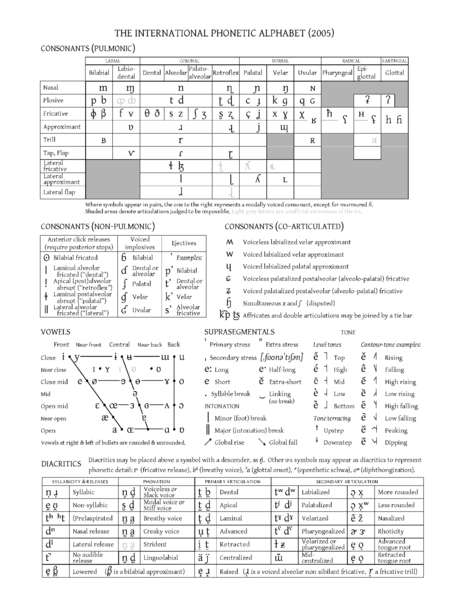
国际音标
国际音标(The International Phonetic Alphabet,简称 IPA),早期又称万国音标,是一套用来标音的系统,以拉丁字母为基础,由国际语音学学会设计来作为口语声音的标准化标示方法。国际音标的使用者有语言学家、言语治疗学家、外语教师、歌手、辞书学家和翻译学家等人。
按照国际音标的设计,它只可以分辨出口语里下列音质的对立成分:音位、语调以及词语和音节的分隔。若要表示诸如咬牙、咬舌和由唇颚裂所发出声音的音质,则有另一套获广泛使用的国际音标扩充系统(由国际语音学学会设计)。
直到2007年,国际音标共有107个单独字母,以及56个变音符号和超音段成分。国际语音学学会偶尔会增删一些符号,或者修正某些符号。
编制类型
国际音标的原则为一个音(或音段)一个符号。这表示,国际音标不会使用两个以上的字母来标示一个声音,除非它可以被视为一两个以上的声音的连续。国际音标通常也不会使用不同的字母来标示两个音,如果没有一个已知的语言将这两个音视为不同的音(选择性),且亦不会使用标示复音节的字母,如 <x> 在英语里表示 [ks] 此一子音复音节。此外,国际音标也没有会因上下文不同而不同音的字母,如英语(及其他大多数的欧洲语言)里的 <c> 。
国际音标的符号共有107个用来标示子音和元音的字母、31个用来更加细化声音的变音符号以及19个标示如音长、声调、重音与语调等的超音段成分。
国际音标中的一些与拉丁字母相同的辅音如 [p], [b], [t], [d], [k], [g], [m], [n], [f], [v], [s], [h], [z], [l], [w] 等已经为许多欧洲语言所使用的字母,在发音上与英语并无差别,而与拉丁字母相同的元音符号[a], [e], [i], [o], [u],它们的发音法则较接近西班牙语或意大利语中的发音,如[i]的发音为英文 piece 中的 i,而 [u] 为英文 food 中的 oo。
其他一些音标虽然与拉丁字母相同,如[j], [r], [c], 和 [y],它们的发音却和一般英语中的发音不太一样,而是来自其他的语言,例如 [j] 要发英语 yoke 的 y(等同德语或荷兰语的 j),而 [y] 的音却反而是和斯堪的那维亚语或古英语的 y 发音一样(等同于拼音的ü/yu/iu、粤语的于jy1、芬兰语的 y、德语的 y 或 ü、法语的 u,或荷兰语的 uu)。其主要的标音原则是一个符号代表一个音,因此不会有像英语中 sh 和 th 这样,两个子音字母组合来代表一个音的情况发生。
在国际音标表里,我们所看到的一些和拉丁字母相似,而只经过稍微改变的符号,它们的发音都很相似,例如卷舌音 ɳ 和齿龈音的 n,它们的发音及符号标示都差不多,除了前者右下角有向右的小勾,代表它是一个卷舌音。
附加于字母的变音符号(附加符号)则为每个语音做额外的描述,如下标 ̥ 加在子音之下,如 n̥ ,说明它是一个无声子音(清辅音)。另外还有一些特别的符号负责描述超音段的语音特征如重音、语调和声调,如元音后的 ː 代表此音为一个长元音。
国际语音学学会建议我们在使用这些音标时最好加上方括号("[" 和 "]"),这其中牵涉到语音标示的程度,也就是严式音标(narrow transcription)与宽式音标(broad transcription)的差别,前者以方括号("[" 和 "]")标示,后者用斜线("/")标示,而国际语音学学会之所以这样建议,是因为严式音标在标注时较不会有模棱两可的情况,例如英语 pretzel 在严式音标就是 [pʰɹ̥ʷɛʔt.sɫ̩],但以宽式音标来看,却可以是 /prɛtsl/ 或 /pretsəl/。
国际语音学学会允许会员根据实际需要添加新的符号和修改原有的符号。
符号表
1.辅音
灰色背景的字段代表被判定为不可能的发音组合。
白色背景而无字的字段代表可能的发音组合,但目前未发现含有此音的语言。
2.元音
3.变音附号(附加符号)
变音符号(附加符号)是加在IPA字母周围的小记号,以标示此字母发音需作的变化,或作更精确地的描述。[12]下标变音附号(正常情况下置于字母或符号下方的记号)必须加在在含有降部的字母时,可以改置于字母上方。
当i加上变音附号后,上方的点可能产生混淆时,会使用不含点的i,<ı>。有些IPA符号也可作为附加符号,以描述语言细节:tˢ (擦音除阻), bʱ (漏气音), ˀa (喉音起始), ᵊ (置入schwa), oʊ (双元音化)。
声门的状态可以用变音符号作良好的描述。以下为齿龈塞音由开声门到闭声门的发音: